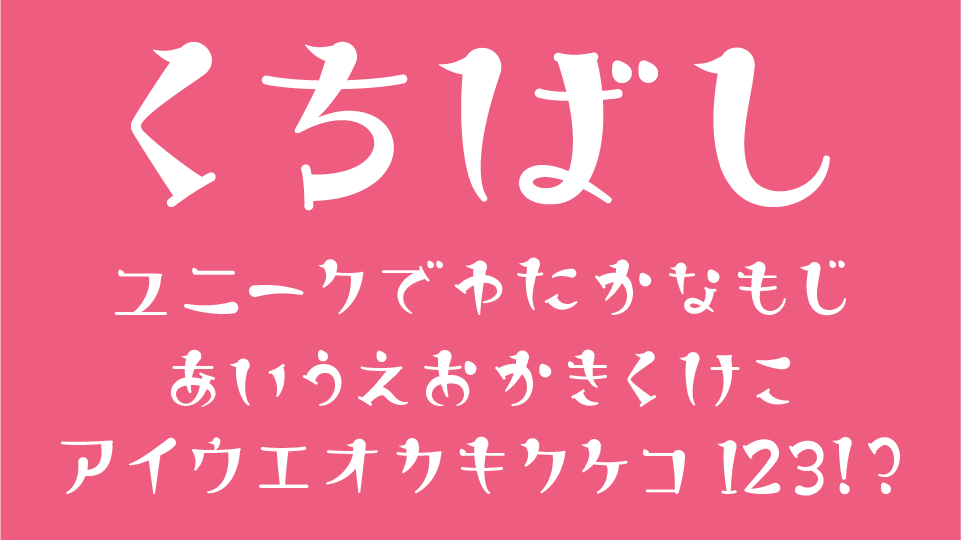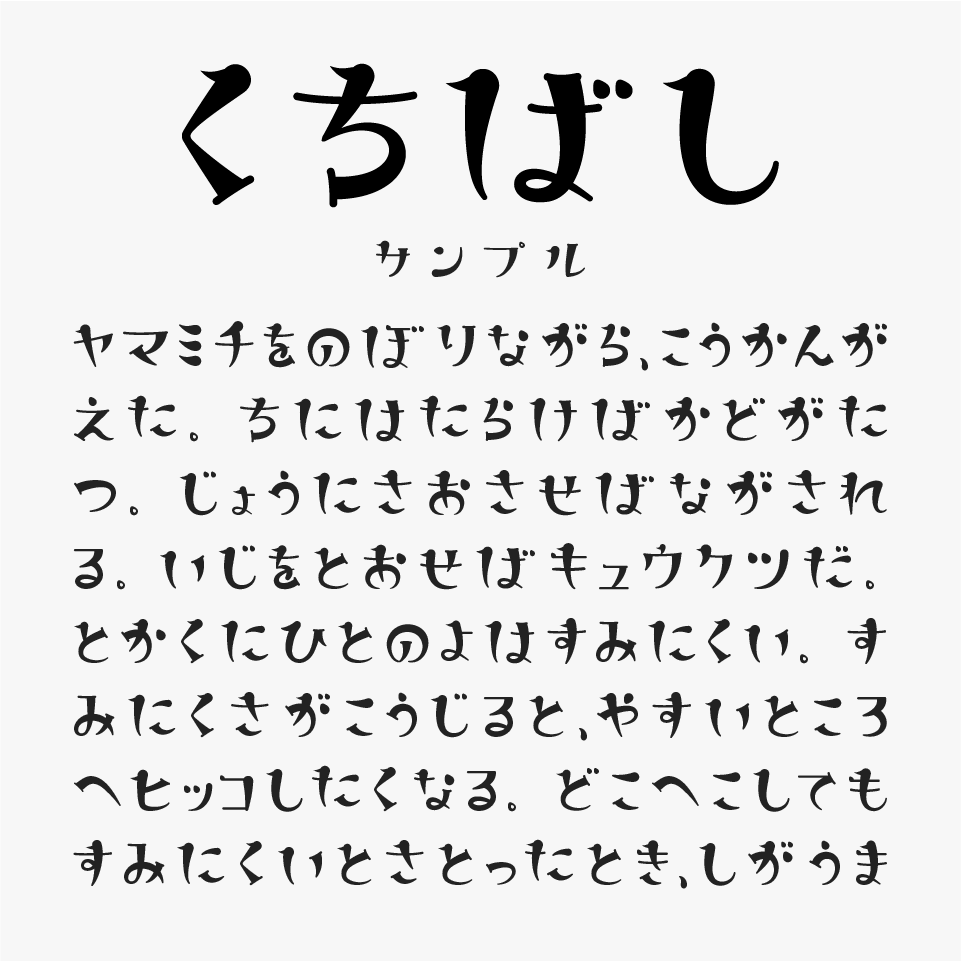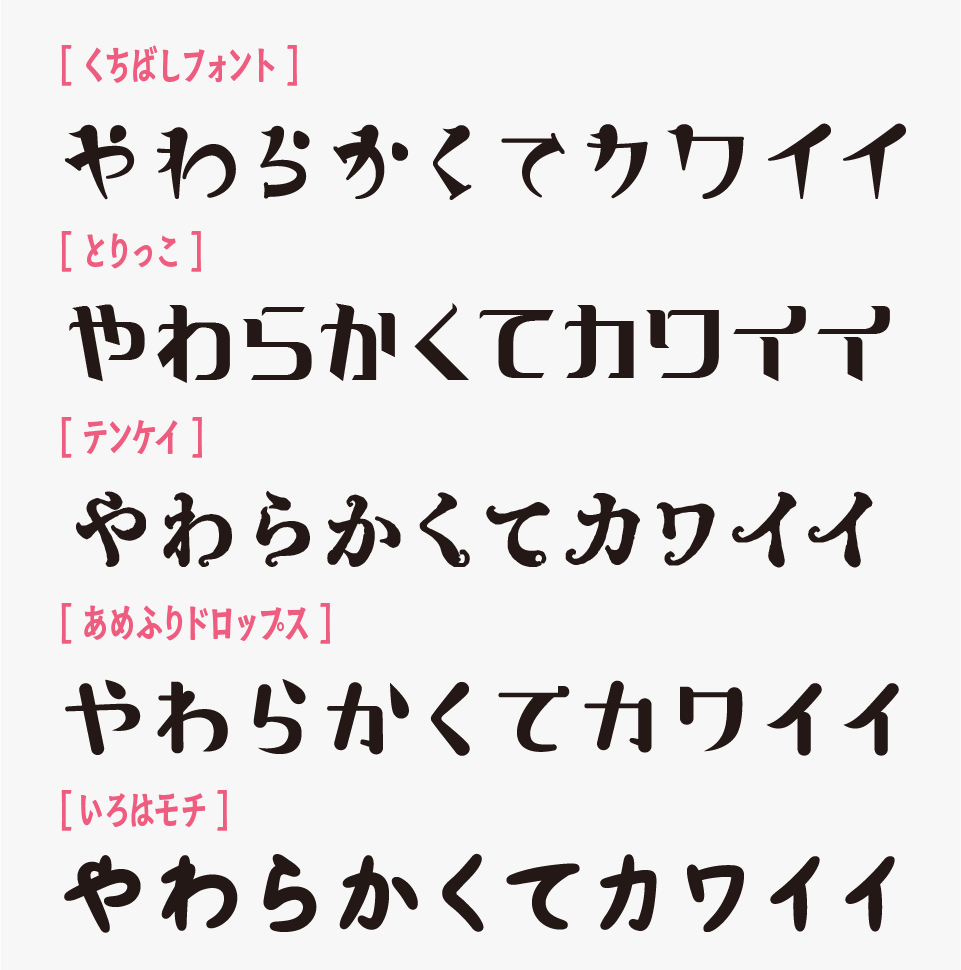
くちばしフォント
くちばしフォントは、小鳥のくちばしを思わせる小さな三角形の飾りを文字の先端にあしらった、遊び心あふれるデザインフォントです。
一文字ごとにくちばしが随所に個性的なアクセントが加えられており、可愛らしさとクラシカルな雰囲気を兼ね備えています。
童話や絵本、小鳥や自然をテーマにした作品はもちろん、雑貨、カフェ、ハンドメイド作品など温もりのあるデザインにもぴったりなフォントです。さりげない装飾が作品に遊び心と親しみやすさを添えてくれるため、可愛らしさの中にも上品さを演出したい場面で活躍してくれるフォントです。
くちばしフォントを、ほかの遊び心のあるフォントと比較してみると、 デフォルメを強く効かせたフォントが多い中でも、特徴的なくちばし形状をワンポイントとして取り入れているため、クセはありながらも文章として扱いやすいデザインに仕上がっています。
比較フォントは、「とりっこ」「テンケイ」「あめふりドロップ」「いろはモチ」と使用していますが、どれも特徴的な明朝体フォントなので、ぜひあわせてチェックしてみてください。